想让你的设计瞬间充满魔法氛围?素材君我们找到了两款1:1高仿的《哈利波特》标志手写字体!这两款字体完美复刻了电影中的经典风格,让你轻松重现魔法世界的独特魅力。所有字体均可免费供个人使用,赶快下载,为你的作品增添一份神秘与魔力吧!
模仿了《哈利·波特》书名和电影标志中带有闪电状“P”的独特手写风格。这款字体非常适合用于制作粉丝海报、邀请函或任何需要一眼就能看出“哈利·波特”风格的设计。
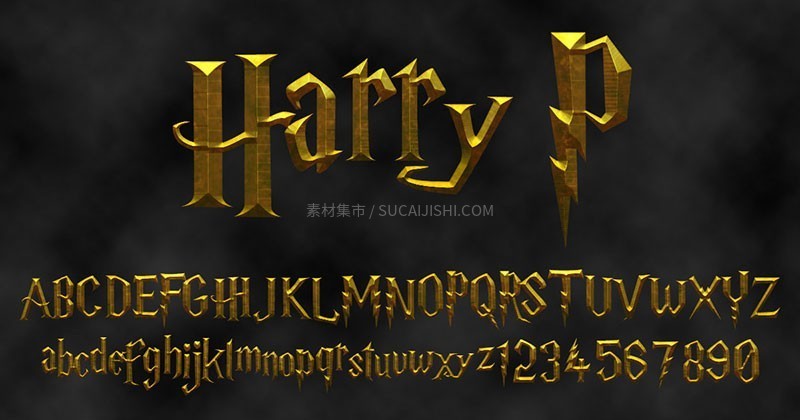
模仿了美国版《哈利·波特》书籍中每个章节标题的字体风格。这款字体带有一种奇幻、古朴的感觉,非常适合用在正文标题或者需要营造魔法世界氛围的文本中。